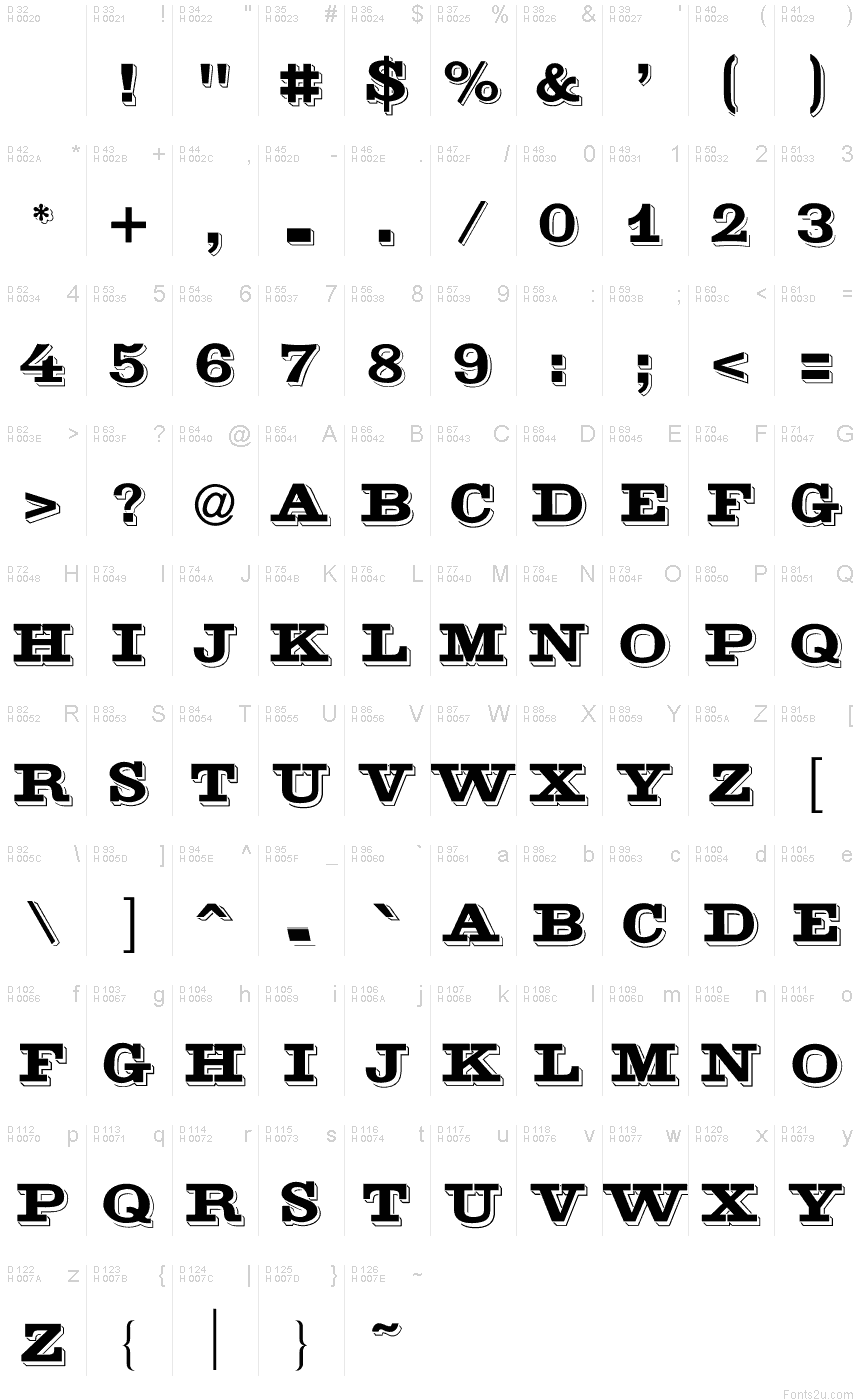
UKIJ 3D od Uyghur Computer Science Association to darmowy, trójwymiarowy font typu slab-serif, który przywodzi na myśl stylistykę dawnych plakatów. Wielkie litery są szerokie i kanciaste, a przesunięte cienie oraz ścięte krawędzie nadają im bryłowaty, trójwymiarowy charakter – wyglądają jak wycięte z materiału, a nie tylko narysowane.
Świetnie sprawdzi się na plakatach, ulotkach, w grafice gier, opakowaniach w stylu retro oraz mocnych nagłówkach, wszędzie tam, gdzie krótkie słowa wymagają głębi. Jako darmowy font, doskonale nadaje się również do plansz tytułowych, monogramów i banerów, szczególnie gdy chcesz, aby litery same w sobie stanowiły efektowną oprawę wizualną.